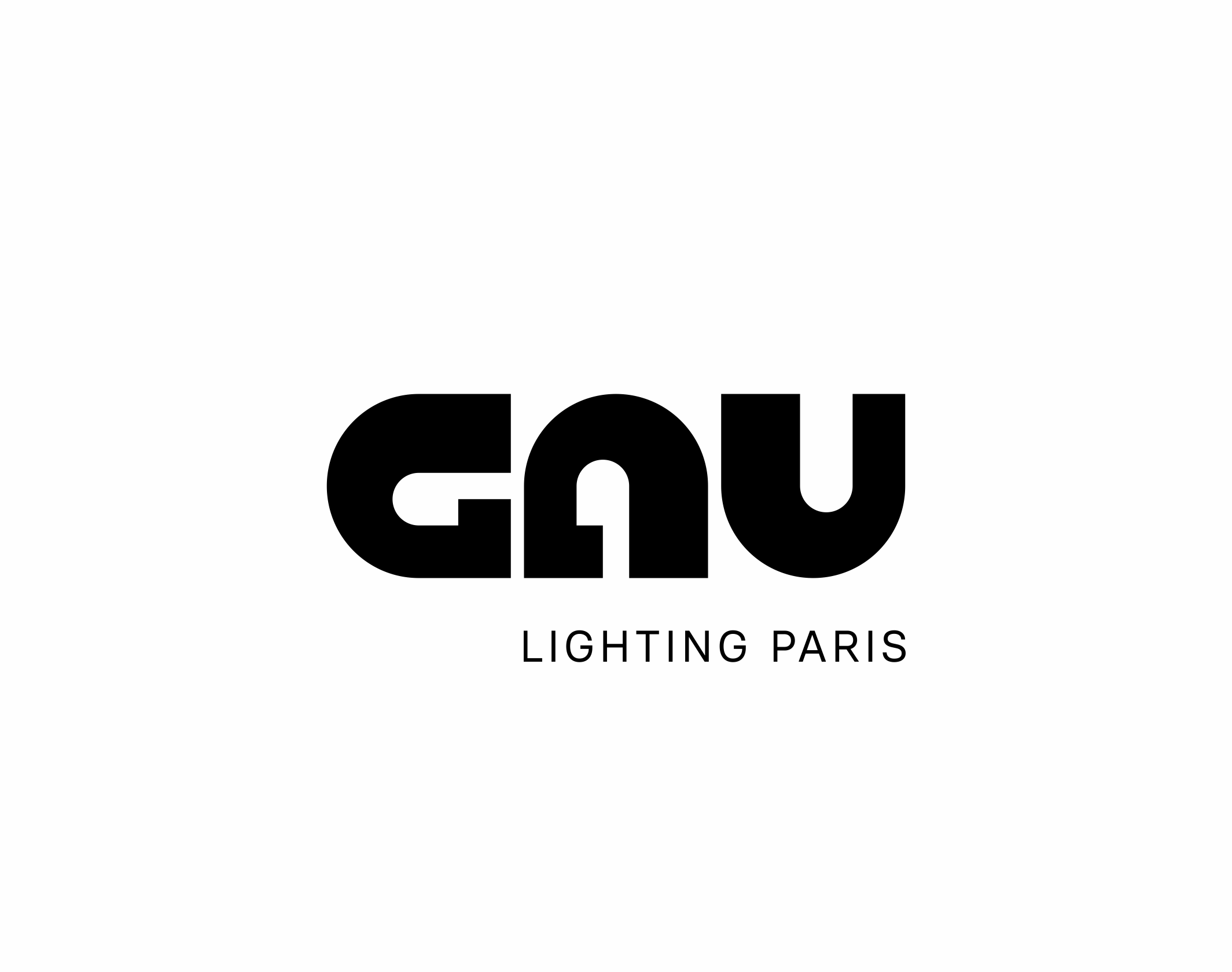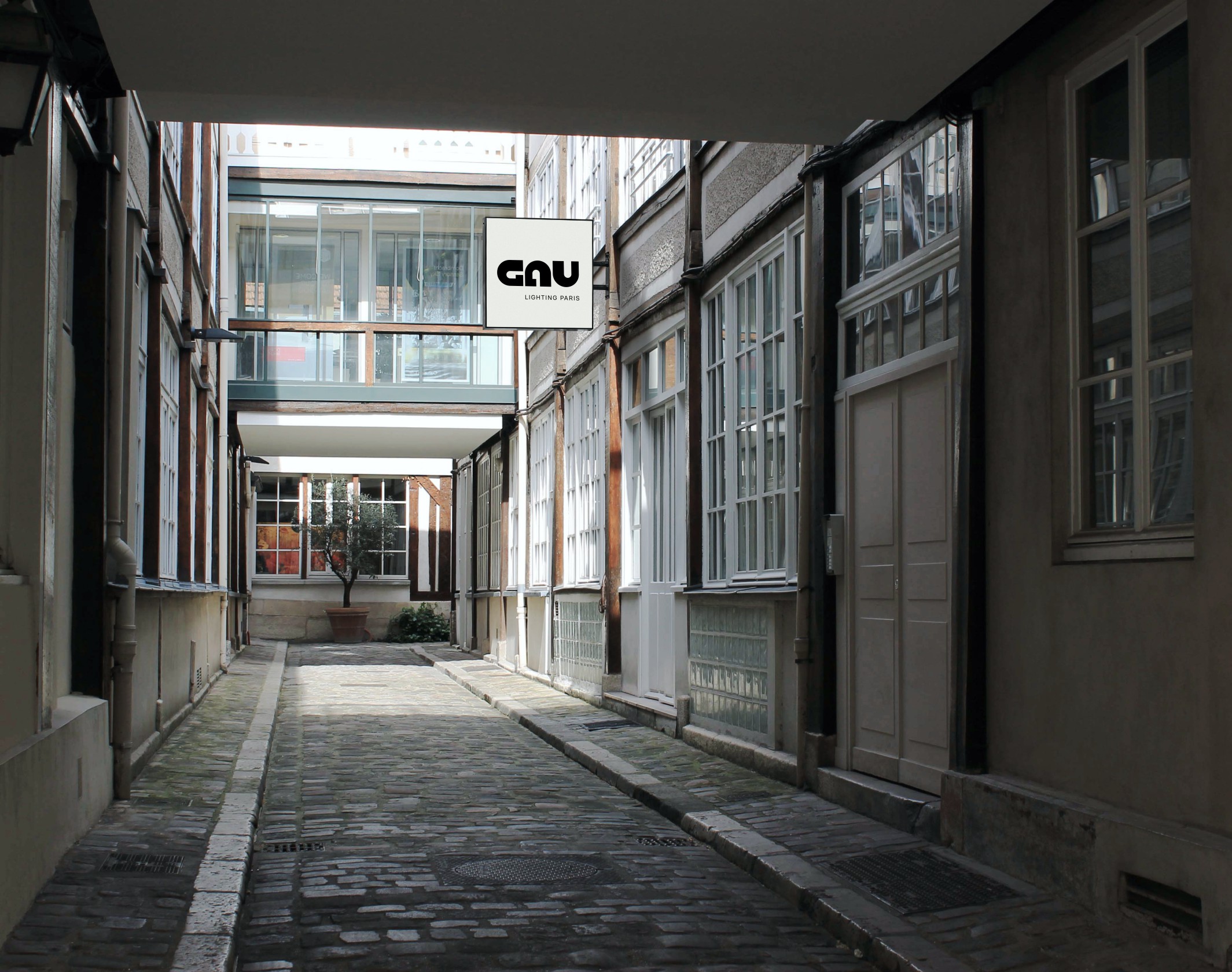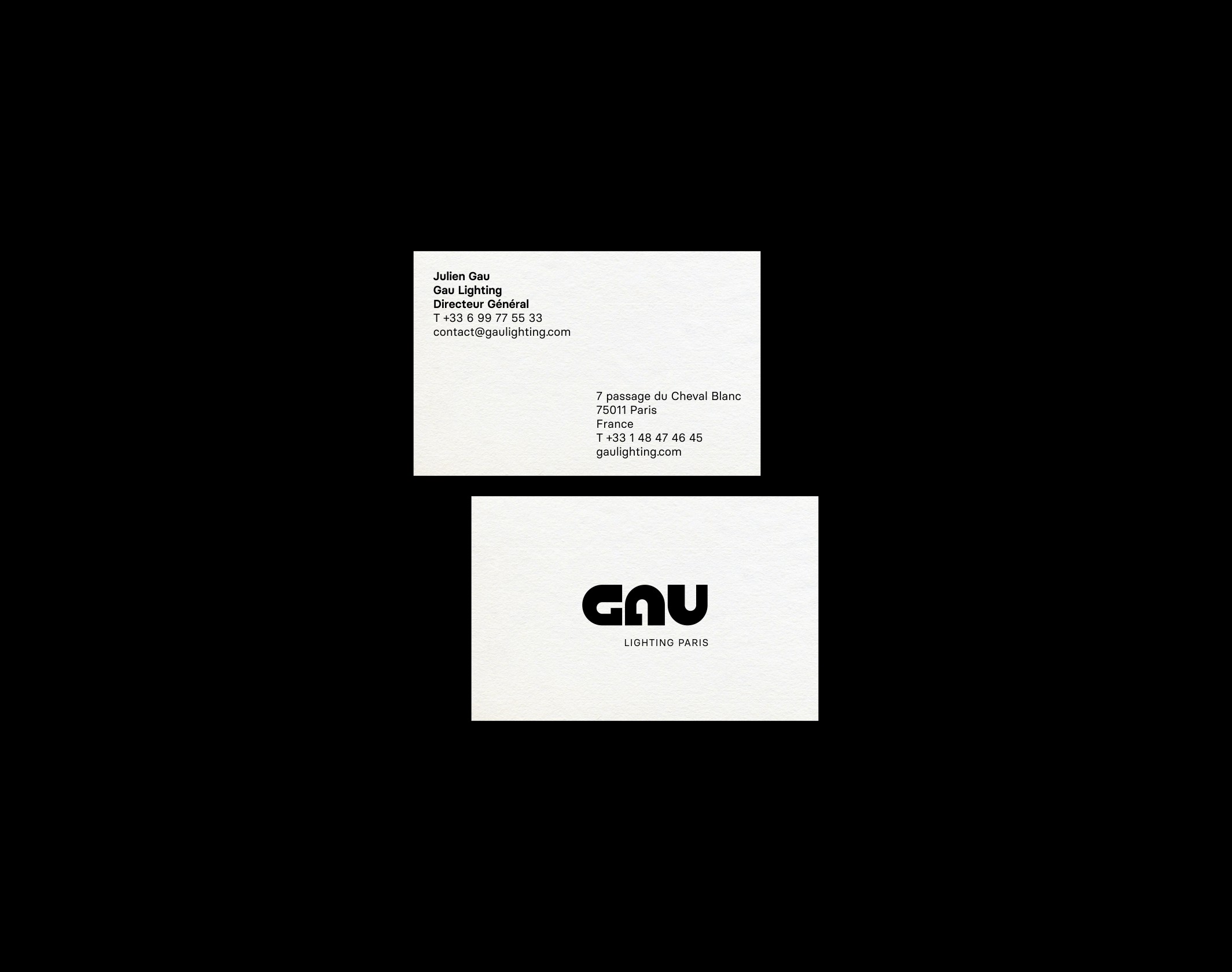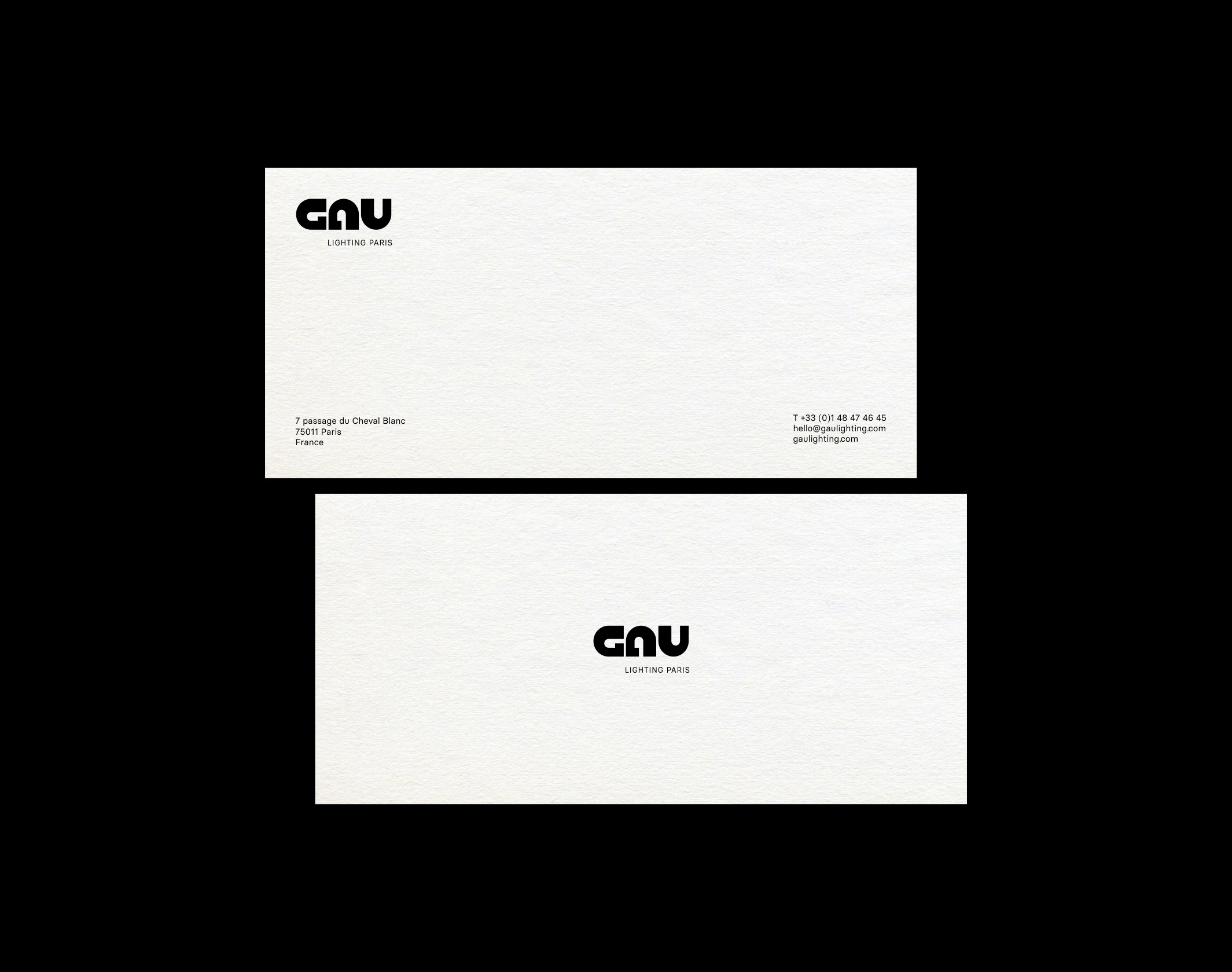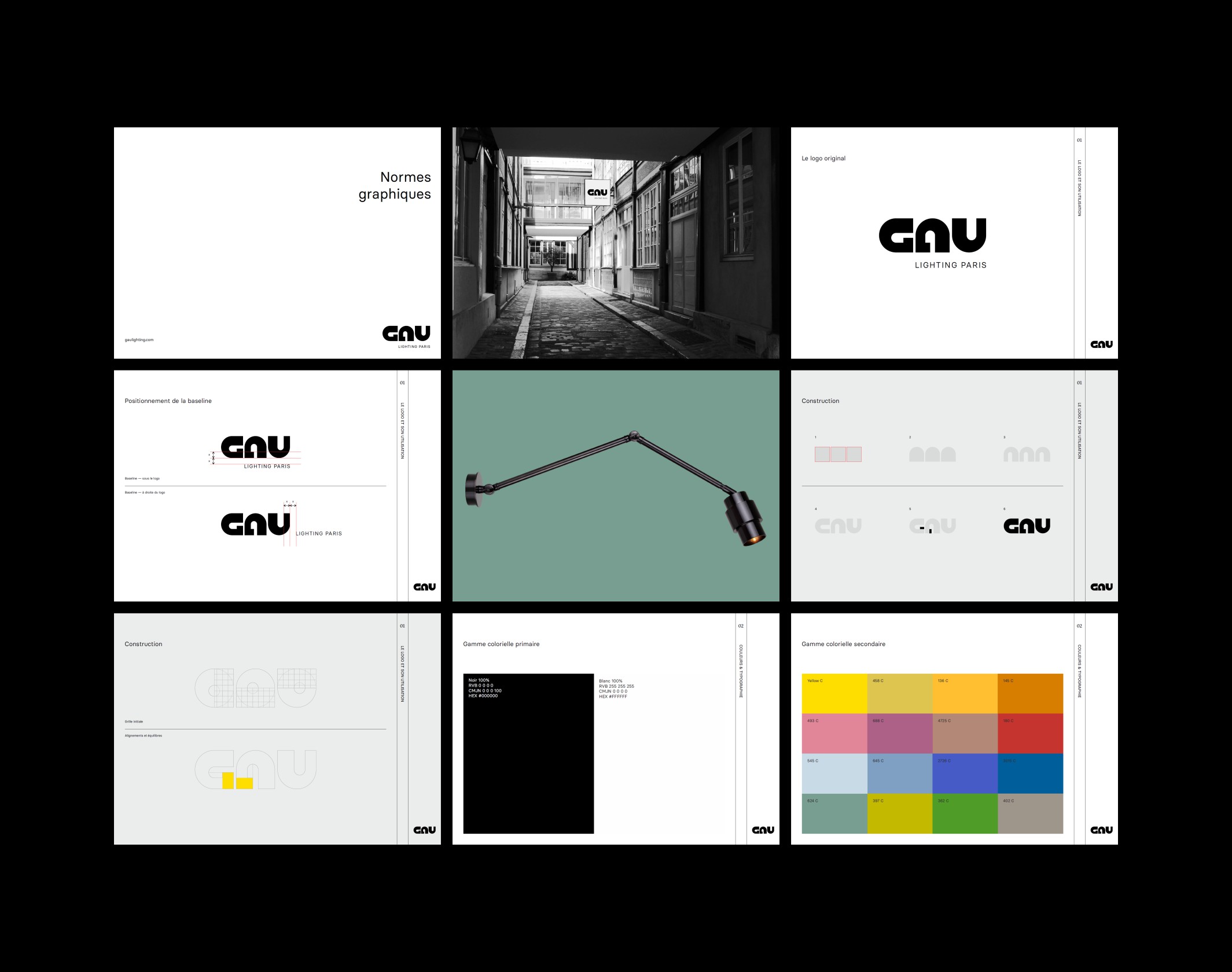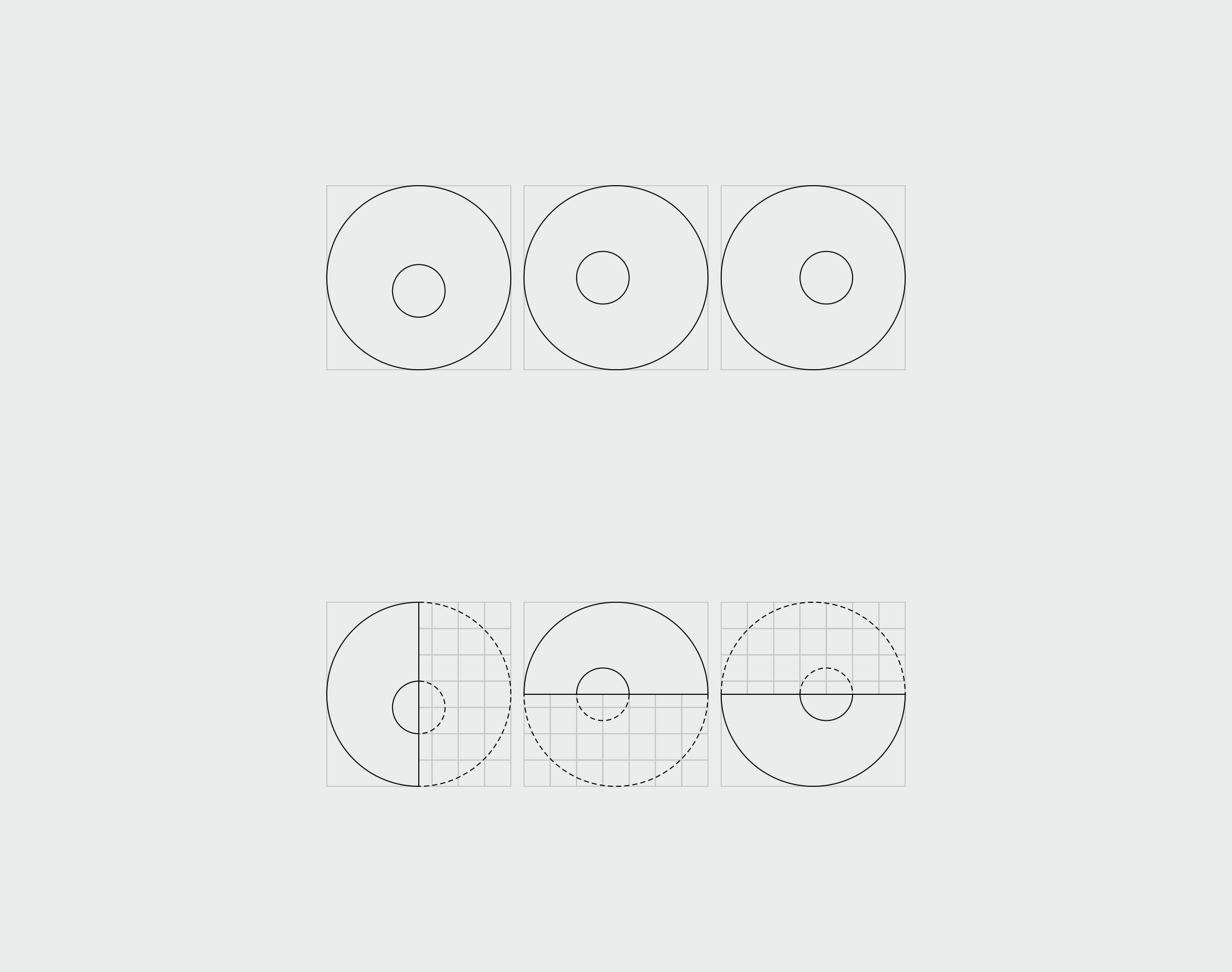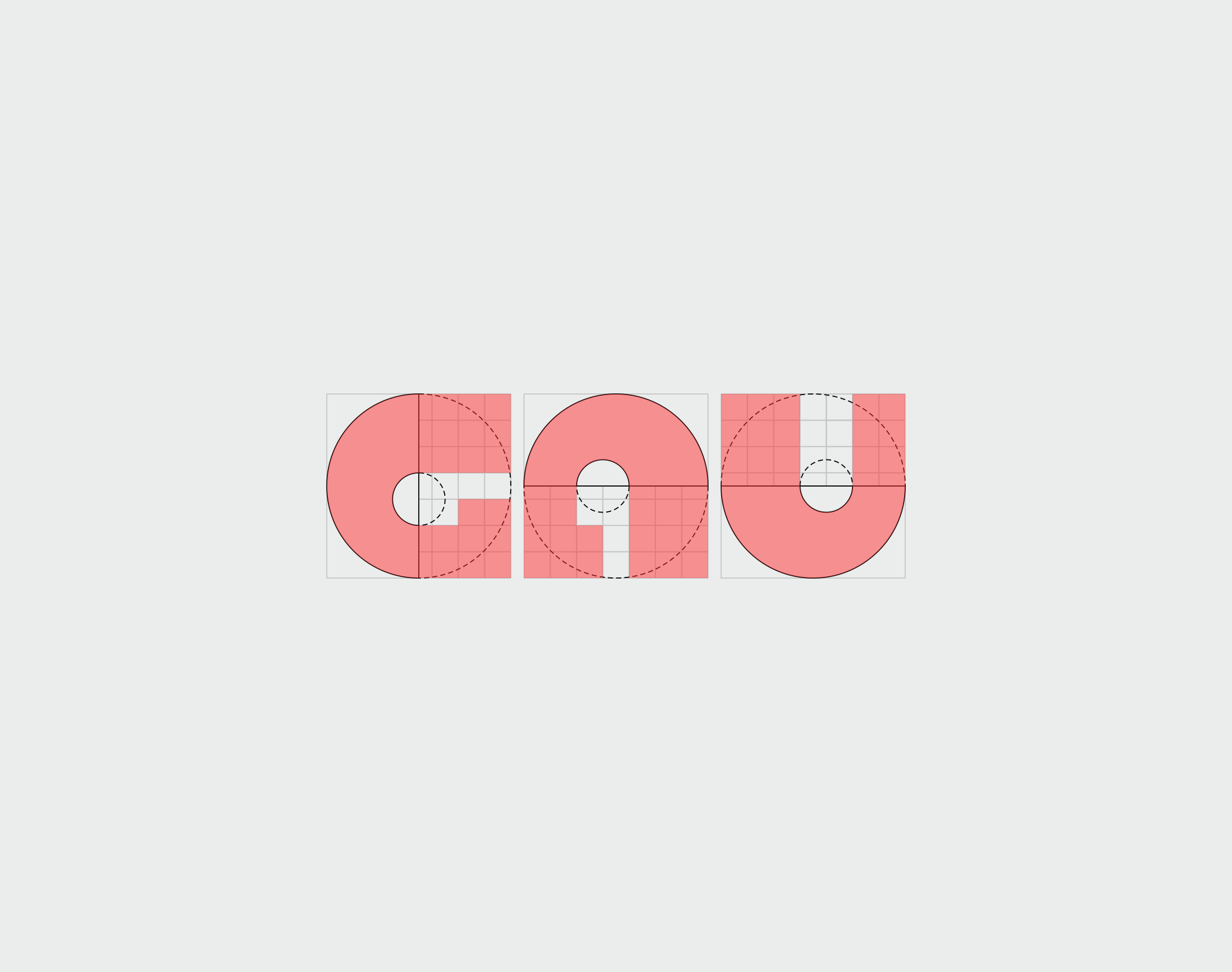
Gau Lighting
Éclairage sur un savoir-faire parisien
Gau Lighting est un fabricant français de luminaires contemporains de luxe, qui travaille depuis 2004 avec les meilleurs designers français et internationaux autour de collections élégantes, principalement à destinationd’hôtels et résidences haut de gamme et de la restauration. Ses modèles se retrouvent dans de prestigieux établissements à Paris, Londres, New York, Cannes ou Marseille, et sont intégralement conçus et façonnés à Paris.
Nous avons aidé la marque à renouveler son identité visuelle, à travers un logo typographique brut et monolithique, dont les 3 lettres ont été dessinées sur la base d’une forme identique. Les codes graphiques élémentaires ont été définis, basés sur une gestion équilibrée de l’espace, des formes et des couleurs qui permet d’alterner entre un langage raffiné et minimaliste, et des visuels dotés d’une présence plus marquée.